오늘은 일러스트레이터를 활용하여
특별한 폰트디자인을 해보려고 합니다.
글자 하나하나가 연결되는 듯한 느낌으로 디자인을 해보려고 하는데요.
폰트말고 도형으로도 활용할 수 있으니
이번에 알려드리는거 잘 활용하시기 바랍니다.
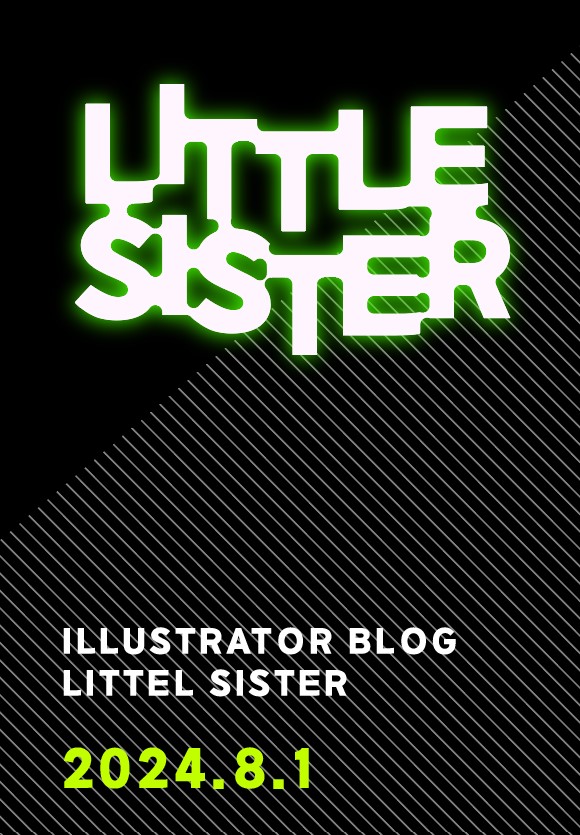
연결되는 폰트를 활용한 디자인
1. 필요한 문구 작성하기
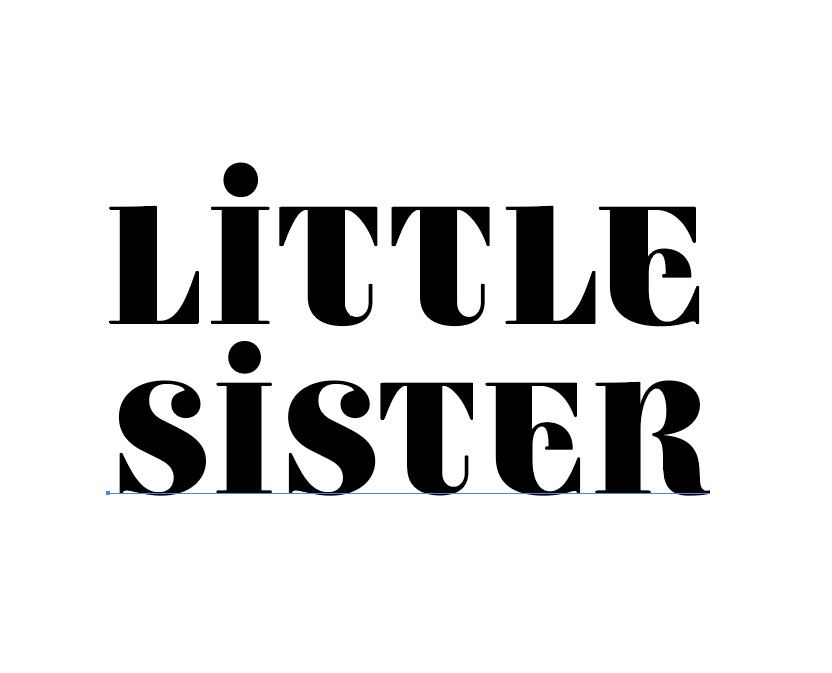
2.폰트 윤곽선 만들어서 그룹을 풀어주세요.
3.창-패스파인더 + 효과-패스-패스이동
그룹이 풀린 글자를 다 잡은 상태에서
창-패스파인더를 꺼냅니다.
그 후 오른쪽위에 세줄버튼 누른고 '컴파운드 패스 만들기'를 클릭합니다.
효과(fx버튼) 누르고 패스-패스이동을 누르면
새로운 창이 열립니다.
총 두번의 패스이동이 들어갑니다. +,- 두번을 하게 됩니다.
7px 둥글게 체크 / -7px 둥글게 체크
그룹된 글자를 더블클릭해서 위치를 옮시면 됩니다.
혹시 잘 안되시면 처음 단계에 글자 그룹풀기를 안하셨을 수 있습니다.
이부분 잘 체크해보시고 다시 진행해보세요!